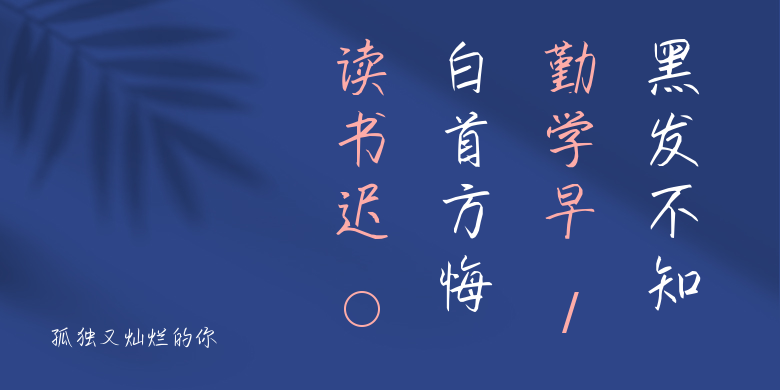
孤独又灿烂的你
孤独又灿烂的你,这款字体结构工整、笔画清晰,兼顾美观与易读性,适用于标题、正文、海报、包装、LOGO 等多种场景。字形优雅稳定,风格百搭耐看,适配日常排版与创意设计,让文字呈现更舒适、更具质感。孤独又灿烂的你一笔一画,皆是细节,以均衡的比例、流畅的线条打造舒适视觉体验,字形端正大气,风格简约现代。无论是商业设计、品牌宣传还是日常排版,都能轻松驾驭,让文字更有格调与力量。孤独又灿烂的你字体下载。